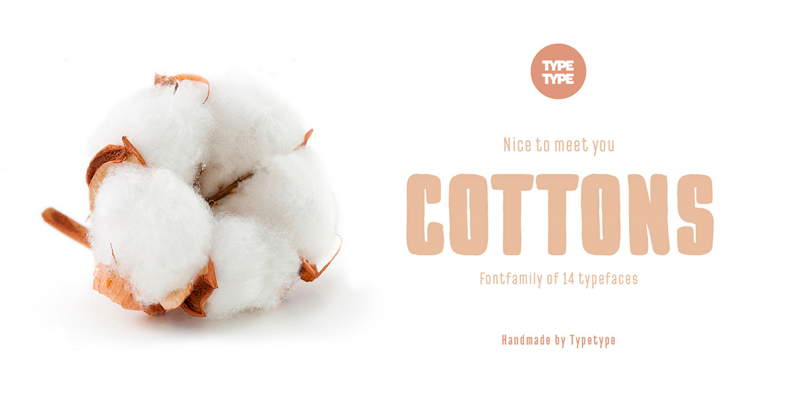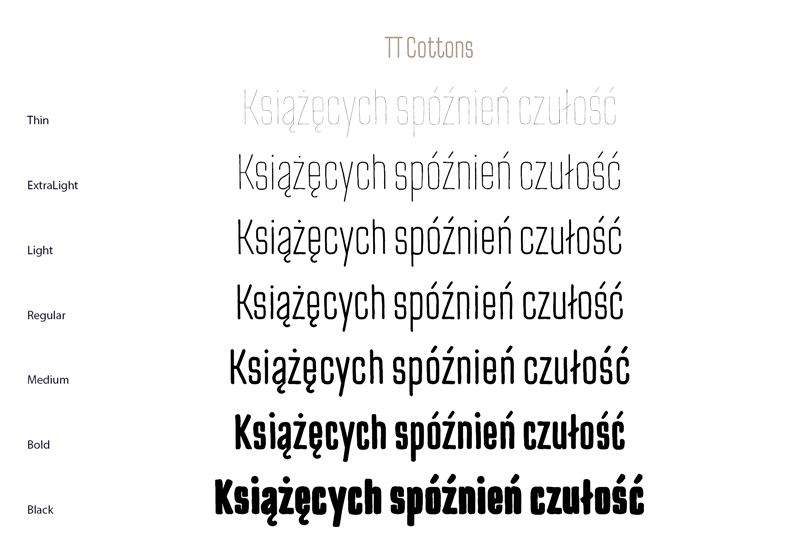
Font Cottons
Zakupiliśmy rodzinę ozdobnych fontów Cottons, zaprojektowaną w 2016 roku przez Rosjanina Ivana Gladkikh. Font zawiera polskie znaki diakrytyczne, ma 7 odmian grubości i italiki.
Font ma ciepły charakter i kojarzy się z pracami wykonywanymi ręcznie, więc znajdzie doskonałe zastosowanie w Mollie, projektowanym przez nas czasopiśmie .